Лучший шрифт для сайта – Встречаем: 15 лучших безопасных веб-шрифтов
Встречаем: 15 лучших безопасных веб-шрифтов
Одной из главных задач веб-дизайна является подбор правильных стандартных шрифтов. Сервисы для внедрения шрифтов, такие как Google Web Fonts или Typekit, были созданы в качестве альтернативы с целью предоставить что-то новое.
Их очень просто использовать. Рассмотрим в качестве примера сервис Google Web Fonts.
Выбираете шрифт Open Sans, Droid Serif или Lato. Пишите код и вставляете его в элемент <head> HTML-документа. Все готово, чтобы ссылаться на него в CSS! Весь Процесс занял не более 60 секунд. Причем все совершенно бесплатно.
Какой-то шрифт может быть доступен не для всех. А это означает, что могут проблемы. Вы довольны тем, что выбрали красивый шрифт для сайта, а посетитель веб-страницы видит вместо него безобразную писанину.
Такого не случится, если реализовать резервный вариант.
Насколько важно применение безопасных веб-шрифтов?
У каждого устройства есть собственный набор предустановленных шрифтов. Какой именно, зависит от операционной системы. Беда в том, что между ними есть небольшие различия.
А сайты? Например, этот? Шрифт, который видите вы, может быть вовсе не тем, который изначально прописан для сайта.
Что это значит? Допустим, что дизайнер выбрал для сайта какое-то семейство платных шрифтов. Если у вас они не установлены и не предоставляется специальным веб-сервисом, то шрифт, который вы видите, — один из стандартных вариантов. Например, Times New Roman.
Поэтому как на вашем экране текст может выглядеть просто ужасно.
А вот стандартные шрифты для сайта есть во всех операционных системах. Это небольшая коллекция, доступная в Windows, Mac, Google, а также Unix и Linux.
С помощью этой подборки дизайнеры, а также владельцы сайтов могут указать, какой именно шрифт следует применить в качестве резервного. Таким образом, появляется возможность контроля над тем, как будет выглядеть страница на разных устройствах.
В качестве запасного варианта разработчик подбирает шрифт, очень похожий на оригинальный, и именно он будет продемонстрирован пользователю.
Взглянем на подборку самых популярных стандартных шрифтов HTML.
Считается стандартным в большинстве случаев. Самый распространенный из шрифтов «sans serif» или рубленых шрифтов (у которых нет засечек на кончиках букв). Его часто используют в Windows для замены других литер.
Helvetica — палочка-выручалочка для дизайнеров. Этот стандартный веб шрифт работает практически всегда (по крайней мере, в качестве подстраховки для других шрифтов).
Выполняет ту же роль для шрифтов с засечками, что и Arial для тех, что без засечек. Он является одним из самых популярных на Windows-устройствах. Это обновленная версия старого шрифта Times.
CSS стандартный шрифт Times знаком большинству. Многим он запомнился по маленьким буквам в узких колонках старых газет. Самый обычный, ставший традицией, вид печати.
Похож на Times New Roman и применяется в качестве разновидности старой классики. Он также считается моноширинным шрифтом. В отличие от шрифтов с засечками и без, все его знаки имеют одинаковую ширину.
Старый шрифт фиксированной ширины, который используется в качестве резервного почти на всех устройствах и операционных системах.
Verdana может по праву считаться истинным веб-шрифтом (true web font) благодаря простым линиям, выступающим в роли засечек, а также большому размеру. Его буквы слегка вытянуты, поэтому легко читаются на экране.
Стандартный web шрифт Georgia формой и размером напоминает шрифт Verdana. Его знаки больше, чем у других шрифтов того же размера. Но лучше не применять его в паре с другими. Тот же Times New Roman, по сравнению с ним выглядит словно карлик.
Palatino относится к эпохе ренессанса. Никаких шуток. Это еще один крупный шрифт, который идеально подходит для интернета. Обычно он используется в заголовках и рекламе.
Еще один старинный шрифт, который появился еще в 16 веке в Париже. Его новая и улучшенная версия входит в комплект стандартных в большинстве Windows-устройств. Позже данный шрифт был взят на вооружение и другими операционными системами.
Bookman (или Bookman Old Style) — один из лучших стандартных шрифтов для заголовков. Его характерная черта — удобочитаемость даже при использовании маленького размера.
Comic Sans MS — забавная альтернатива для шрифтов с засечками.
Это шрифт средневековой тематики, изначально разработанный корпорацией Microsoft в середине девяностых годов. Он применялся в Windows XP. Сегодня с его помощью составляют основной текст.
Аналог стандартного шрифта для сайта Arial. Правда, он больше, толще и жестче. Своими пропорциями он похож на шрифт Helvetica. А это важно. Им можно успешно заменить Helvetica без необходимости покупать лицензию.
Еще один замечательный шрифт для выделения заголовков. Он хорошо смотрится в короткой фразе, состоящей из нескольких слов, а также в длинных предложениях.
35. Stalemate
Stalemate – это изящный рукописный шрифт с некоторым винтажным оттенком. Он подходит для создания акцентов и персонализации вашего сайта.
36. Crimson Text
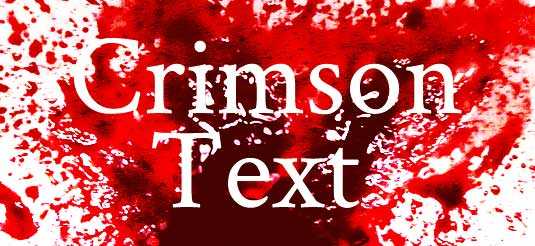
Этот тщательно разработанный классический пропорциональный шрифт может использоваться как для отображения больших объемов текста, так и написания заголовков.